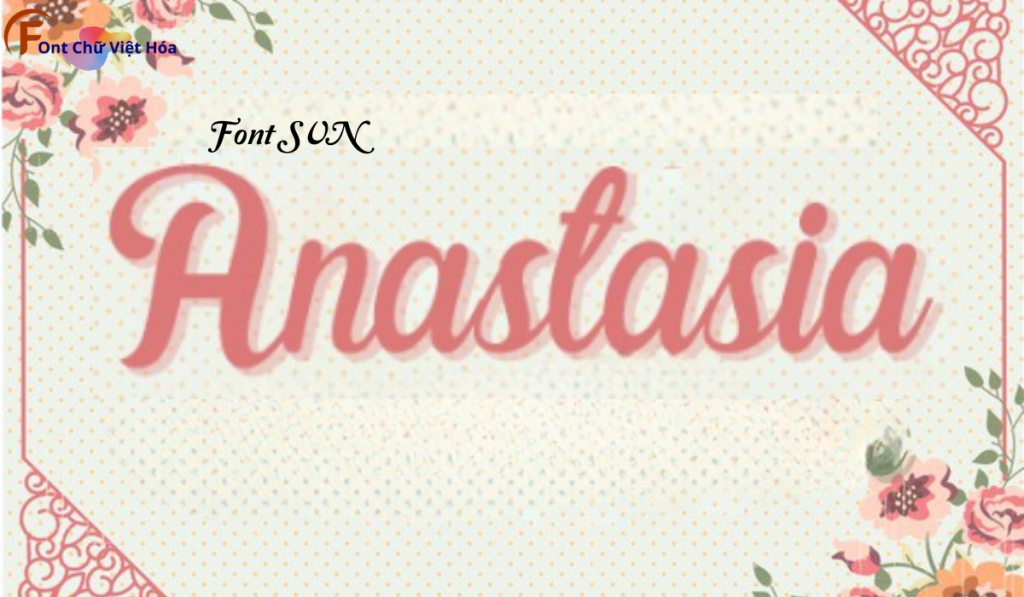
Font SVN Anastasia Việt Hóa
Bộ Font: SVN
Phân loại: Cá tính, Nữ tính
Độ dày: Thường
Font SVN Anastasia Việt Hóa là một font chữ viết tay cá tính, thuộc bộ font SVN. Được thiết kế với mục tiêu mang lại sự mềm mại và thanh thoát, font này lý tưởng cho các dự án thiết kế như thiệp mời, logo, và bao bì sản phẩm. Với các nét chữ uyển chuyển và độ dày đều đặn, Font SVN Anastasia Việt Hóa không chỉ dễ đọc mà còn tạo cảm giác thân thiện và gần gũi. Việc Việt hóa font giúp người dùng dễ dàng sử dụng trong các thiết kế tiếng Việt, mang lại sự tiện lợi và thẩm mỹ cao.